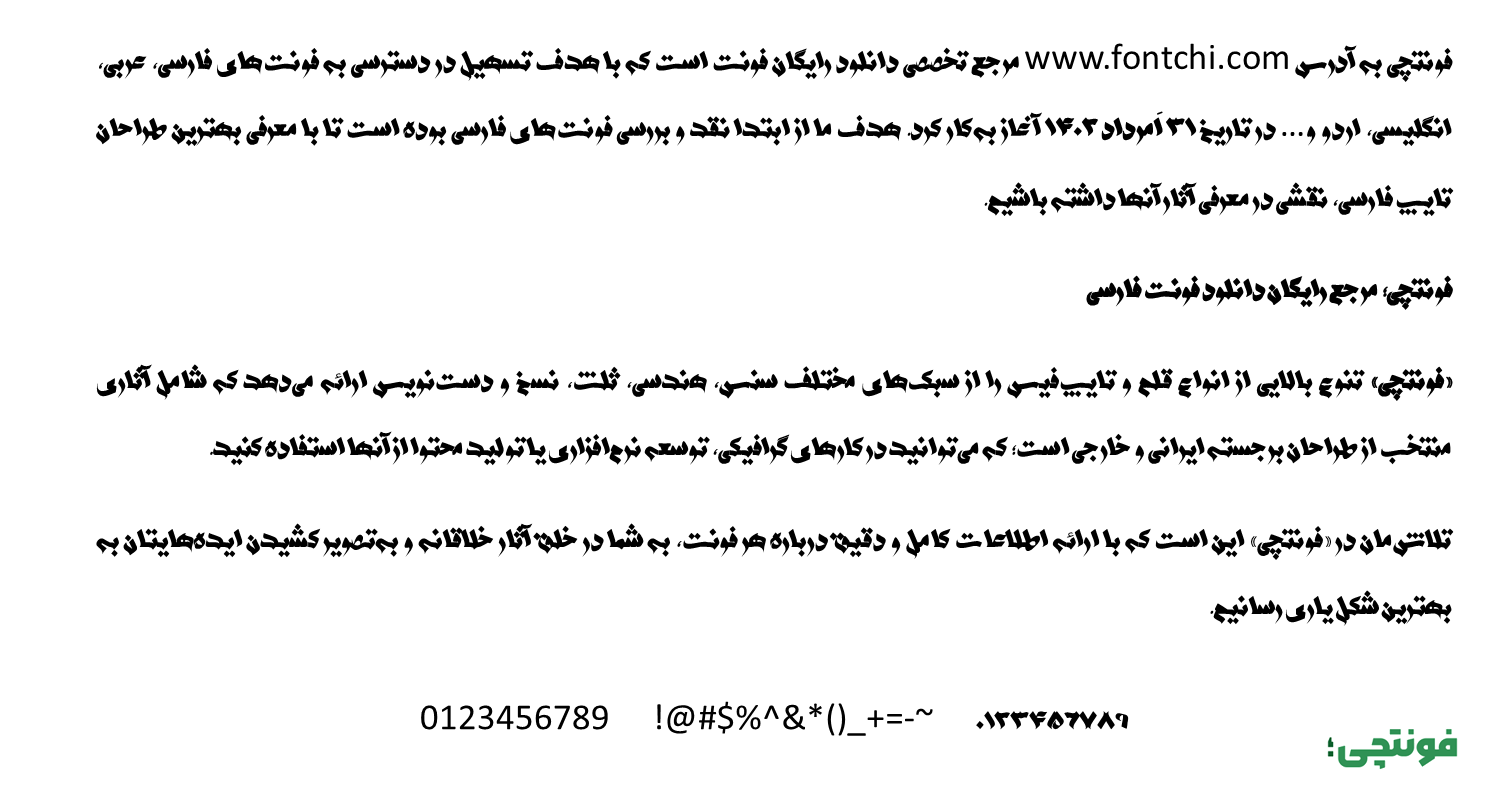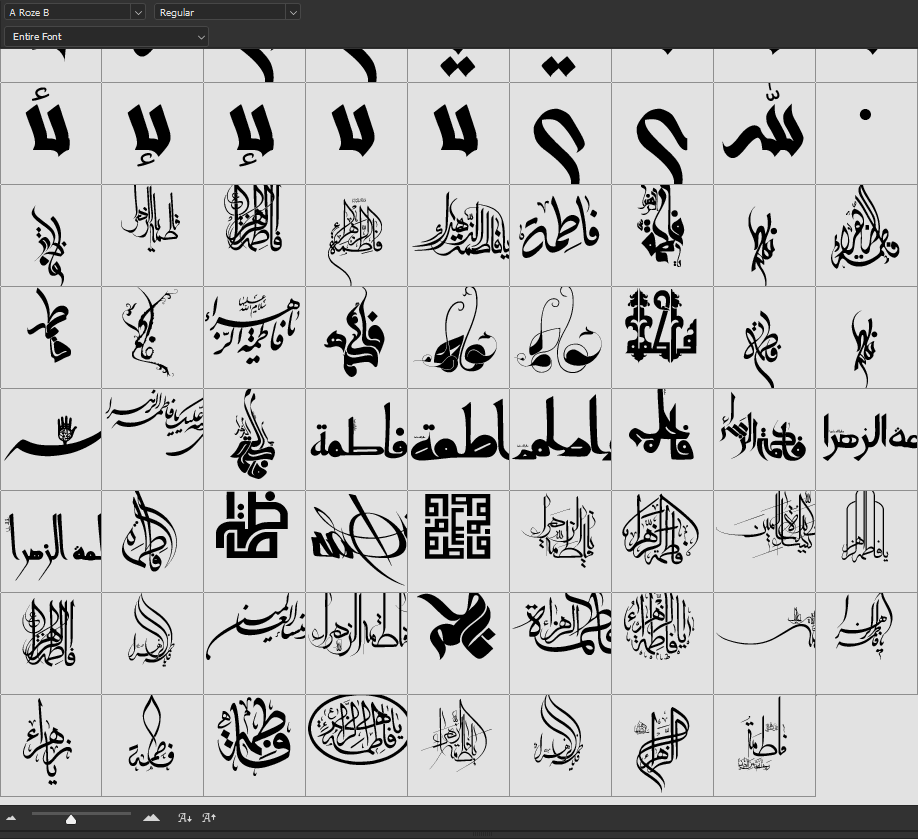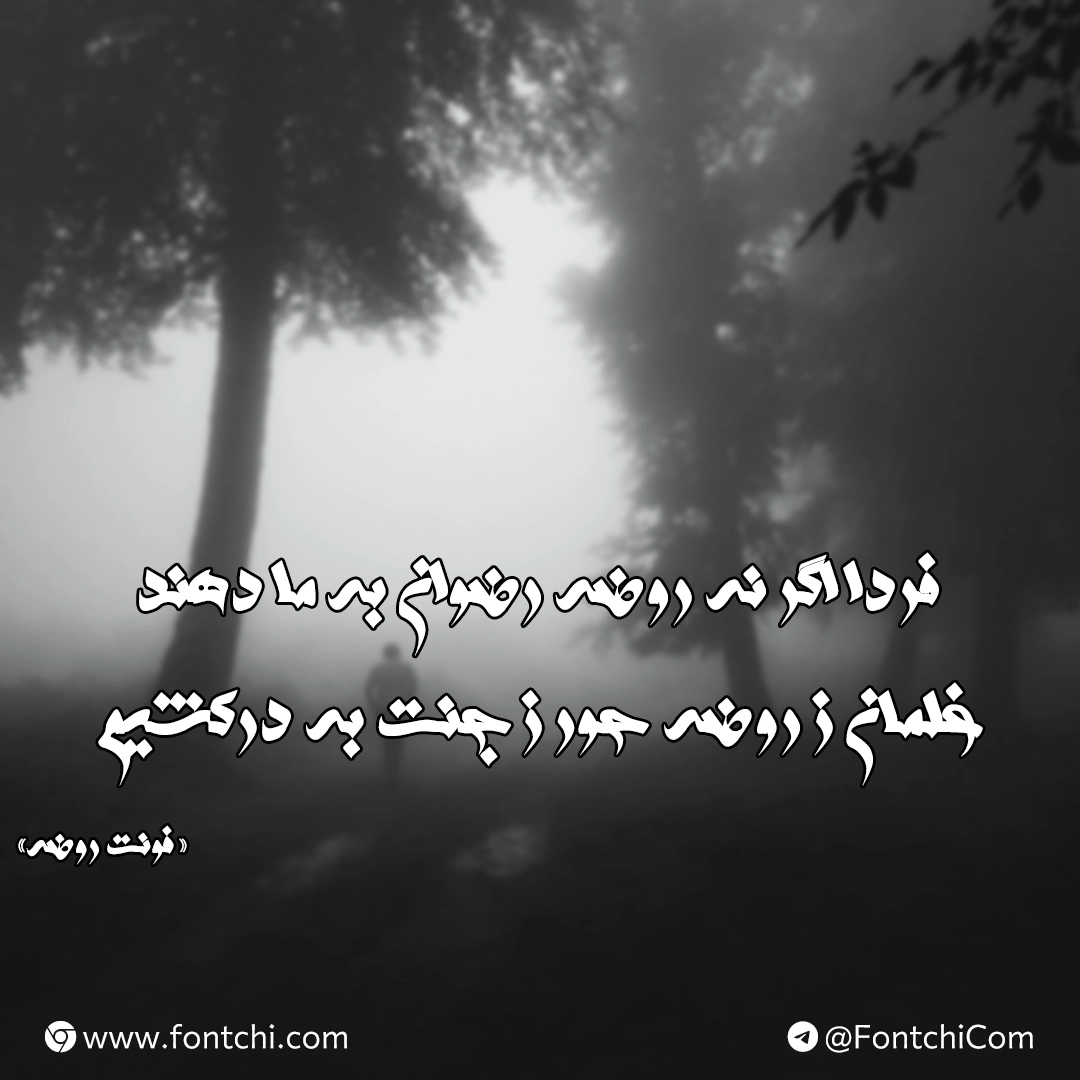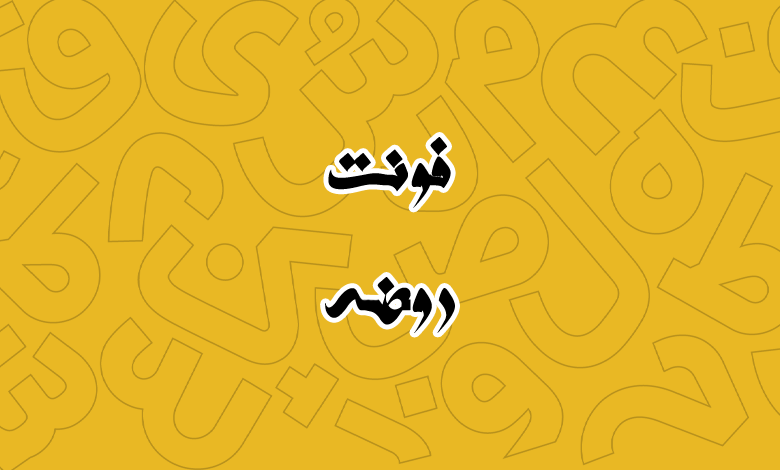
فونت روضه (A Roze)
فونت روضه (به انگلیسی: A Roze) قلمی کاملا گرافیکی و با ظاهری فانتزی است که میتوانید از آن به عنوان یک فونت مذهبی استفاده کنید. این فونت آزاد دارای گلیفهای متعددی برای نام «فاطمه» میباشد. در ادامه با دانلود فونت a roze رایگان با شما همراه هستیم.
فونت روضه توسط علی سواری در یک ساختار گرافیکی طراحی شده است که دارای گلیفهای متعددی برای حروف و ترکیبات جایگزین است تا قلمی نمایشی در کارهای مذهبی داشته باشید. این فونت از دو وزن پشتیبانی میکند که در تصویر زیر پیشنمایش آن را مشاهده میکنید.
با دانلود فونت روضه علاوه بر زبان فارسی، به قلمی دسترسی دارید که از زبان عربی نیز پشتیبانی میکند. کلیه اعراب و حروف برایی هر دو زبان دارای گلیفهای استاندارد خود هستند. برای مثال حروف متفاوت «ک، ی، ه، ؤ، ئ» عربی در این قلم تعبیه شده تا برای استفاده دو زبانه مشکلی نداشته باشید. تنها کاستی این فونت در بخش اعداد است که برای زبان فارسی نیز از اعداد عربی «۰۵۶» استفاده شده است.
در فونت روضه پشتیبانی از زبان انگلیسی به همان سبک طراحی وجود ندارد، اما برای اینکه نیازی به تغییر فونت برای حروف لاتین نباشد، از فونت پیشفرض سیستم عامل استفاده خواهد شد.
طراحی حروف در فونت روضه بهشکلی است که مانند فونت خطاطی بهنظر میرسد. این فونت با اینکه ظاهری هندسی دارد، اما الهام گرفته از خطوط خوشنویسی است. در این فونت شاهد دو وزن زیر هستیم.
- A Roze Normal یا Regular: مناسب برای متون بلند.
- A Roze B یا Bold: مناسب برای متون کوتاه.
در هر دو وزنها کلیه گلیفها به شکل استاندارد تغییر وزن داده شدهاند. از وزن بولد میتوانید برای متون کوتاه و عناوین که جنبه نمایشی دارند استفاده کنید. از دیگر کاربردهای این قلم میتوان در استفاده برای عنوان کتاب (خصوصا کتابهای تاریخی و مذهبی) اشاره کرد.
فونت رایگان روضه برای اینکه ظاهری نمایشیتر داشته باشد، در برخی حروف و ترکیبات دارای حروف جایگزین است که از جمله آنها میتوان به «س، ش، ک، گ، ه، ی» اشاره کرد. همچنین نقطهگذاری در حروف «پ، ث» پایانی طوری است که هر سه نقطه بهصورت افقی کنار هم قرار دارند.
یکی دیگر از قابلیتهای فونت رایگان روضه، پشتیبانی از گلیفهای خاصی با نام «فاطمه» است. از اینرو میتوان از این گلیفها در طراحیهای گرافیکی همچون چاپ بنر، چاپ پرچم و رویدادها استفاده کرد که در تصویر زیر لیست کاملی از آنها را مشاهده میکنید.